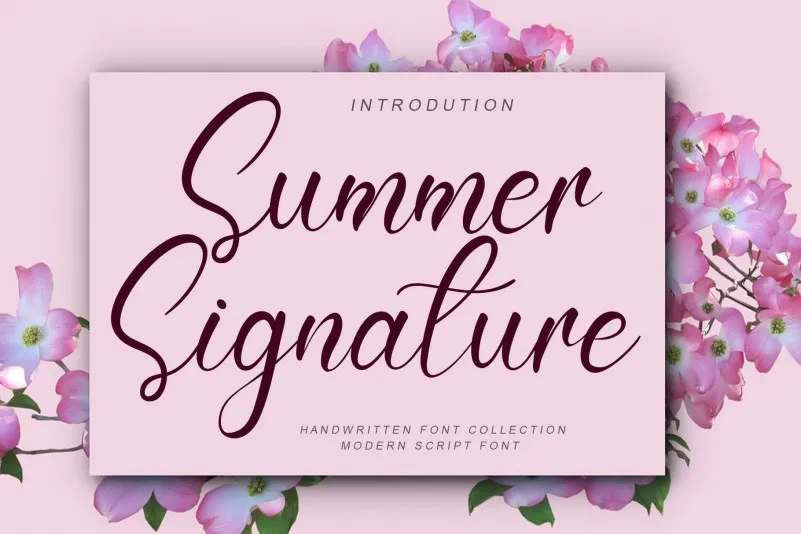
Esta é uma fonte à mão deslumbrante e elegante, perfeita para quem aprecia a delicadeza dos traços humanos. As letras distintas e equilibradas de Summer Signature Font são verdadeiras obras de arte, com um estilo versátil que permite transformar qualquer projeto em algo realmente especial. Seja você criando cartões de aniversário, artigos de jornal, ou simplesmente adesivos personalizados para sua casa, a capacidade única e estilosa dessa fonte o tornará sempre único e inovador na comunicação visual.